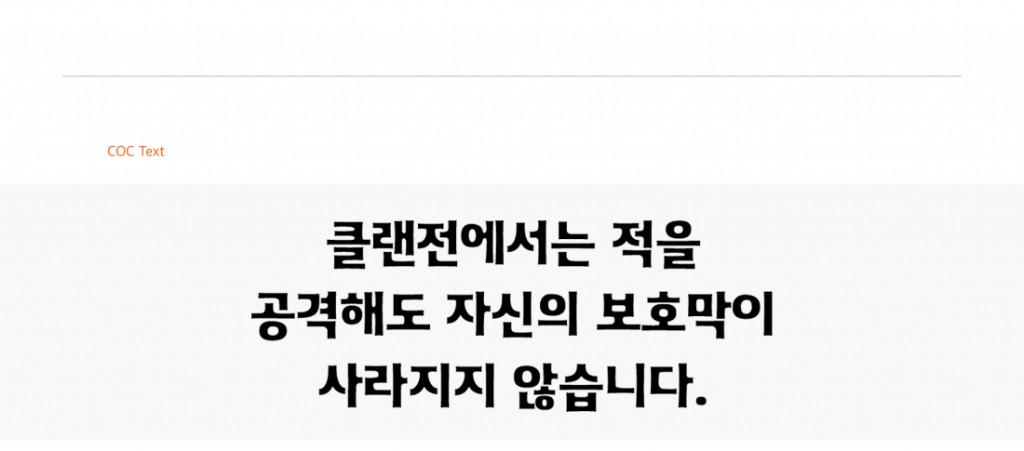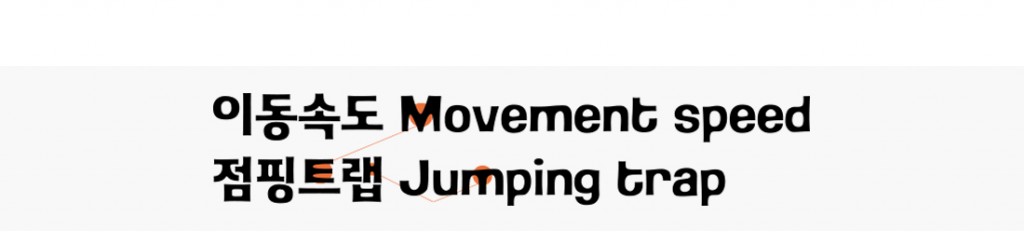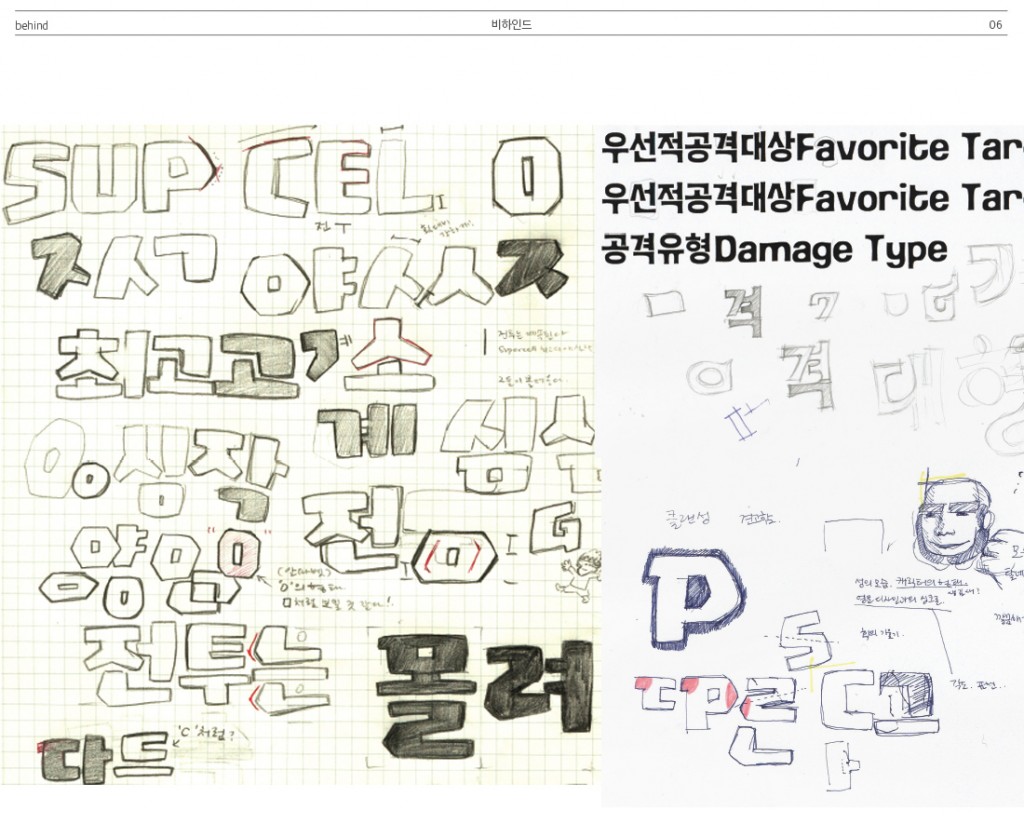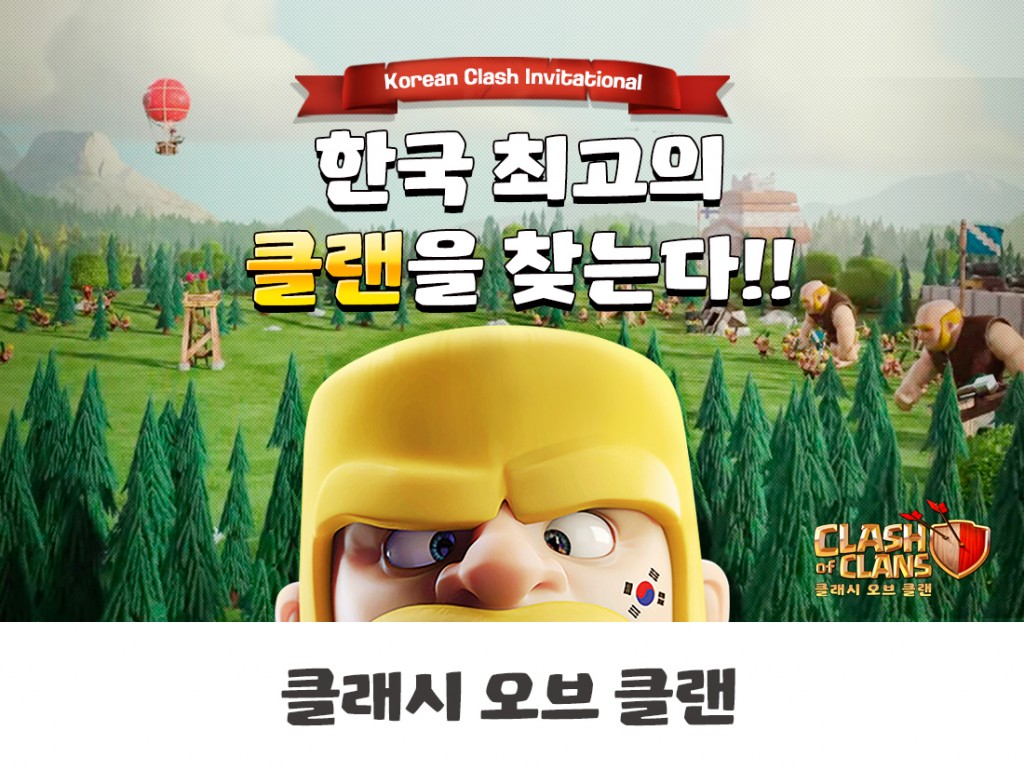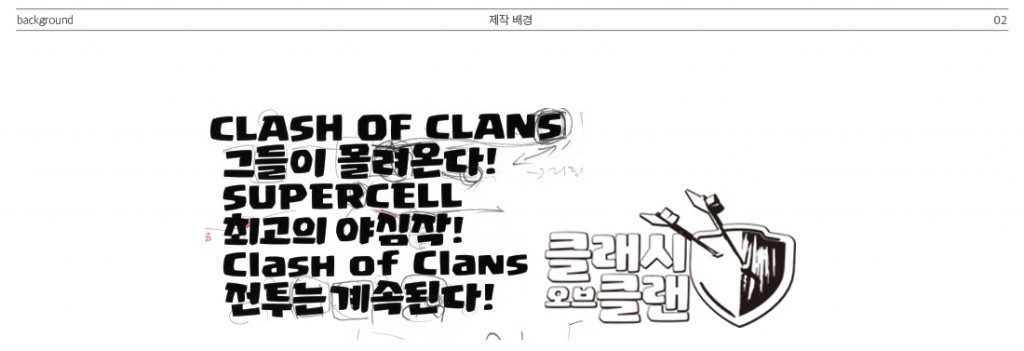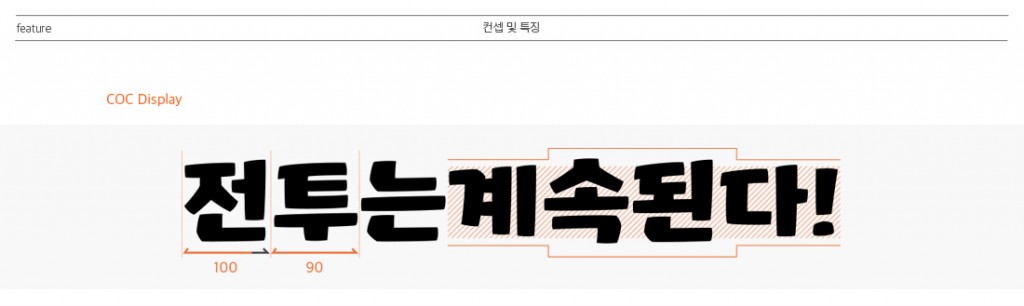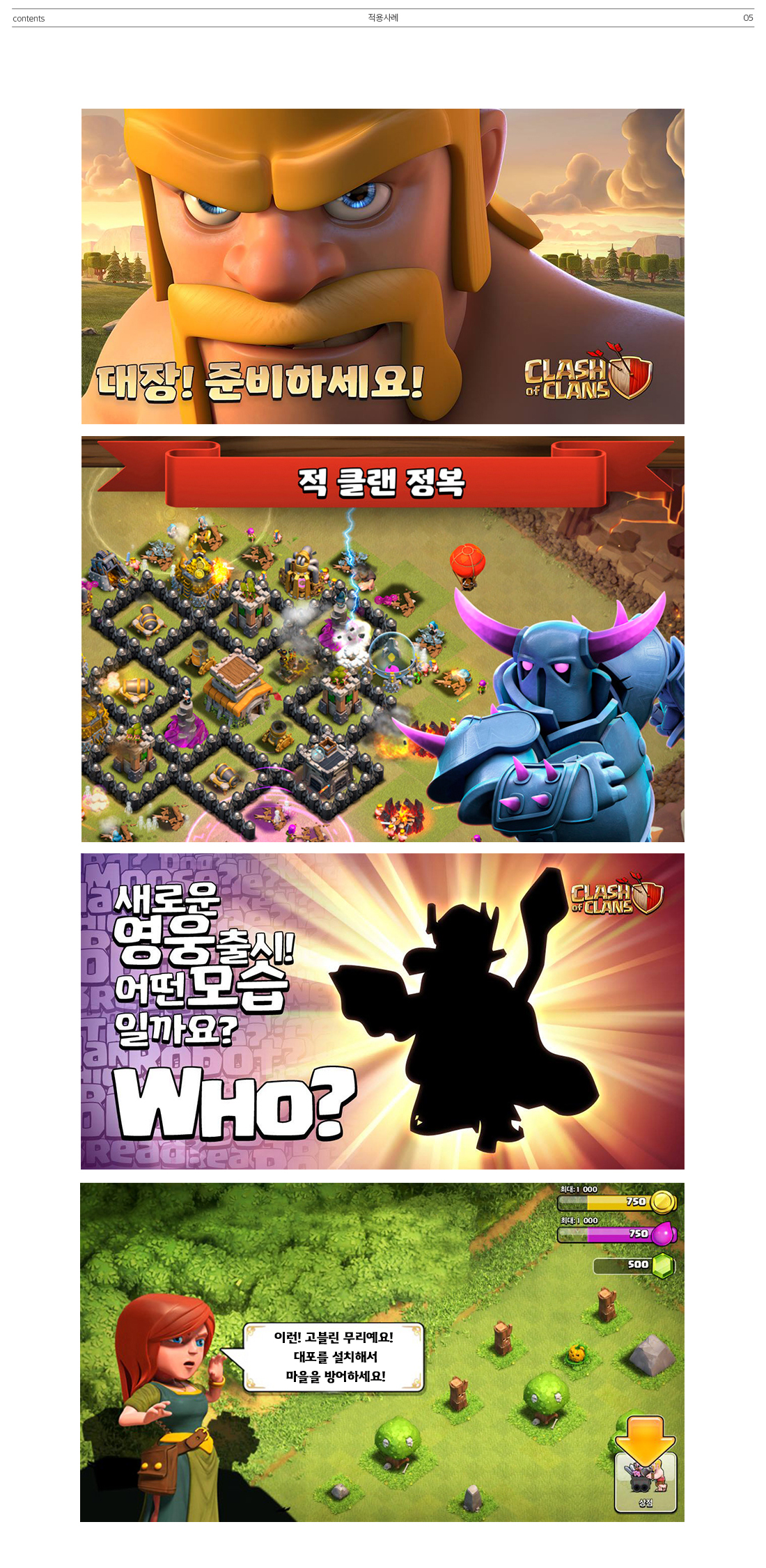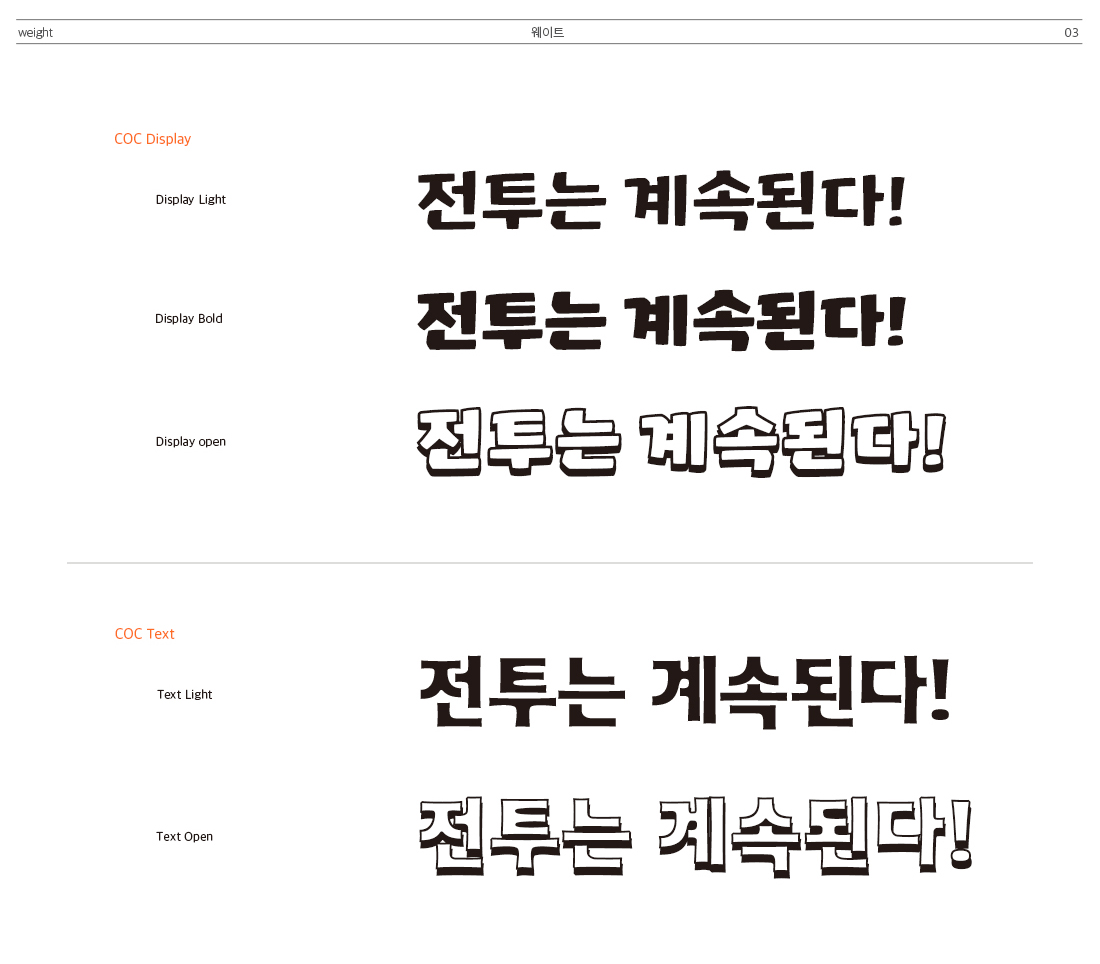
클래시 오브 클랜 : 전투는 계속된다. 폰트도 계속된다!
재치있는 광고나 그래픽으로 잘 알려진 게임 ‘클래시 오브 클랜‘은, 브랜딩을 위해 영문전용서체를 개발하여 효과적으로 사용하고 있었다. 다만, 한글 전용서체는 따로 가지고 있지 않아 게임에서 뿐만 아니라 마케팅에서도 게임의 매력을 잘 살리지 못하는 한계가 있었고, 이를 극복하기 위해 한글 전용서체 제작을 산돌에 의뢰하여 프로젝트가 진행되었다.
타이포브랜딩 : 클래시 오브 클랜 전용서체
클래시 오브 클랜의 전세계적인 히트로 모바일 게임업계를 평정한 슈퍼셀(SUPERCELL). 슈퍼셀은 핀란드의 게임회사로 클래시 오브 클랜 뿐만 아니라 붐비치, 헤이데이 등의 게임을 통해 자신들만의 색깔을 확실히 구축해나가고 있으며, 그들의 대표작 클래시 오브 클랜은 출시한 이래 인기순위 상위권을 놓치지 않고 세계 135개국 유저들이 함께 즐기는 게임으로 발돋움했다.
제작배경
재치있는 광고나 그래픽으로 잘 알려진 ‘클래시 오브 클랜’은, 브랜딩을 위해 영문전용서체를 개발하여 효과적으로 사용하고 있었다. 다만, 한글 전용서체는 따로 가지고 있지 않아 게임에서
뿐만 아니라 마케팅에서도 게임의 매력을 잘 살리지 못하는 한계가 있었고, 이를 극복하기 위해 클래시 오브 클랜과 잘 어울리는 한글 전용서체 제작을 산돌에 의뢰하여 프로젝트가 진행되었다.
컨셉 및 특징
# 모듈
글자폭을 가변폭으로 설정하여 세로획이 많은 글자에서도 두께가 고르게 보이도록 했다. 탈네모꼴 형태이고, 시각기준선을 가운데로 정렬해 리듬감이 돋보인다.
# 자소의 특징
ㄹ, ㅂ, ㅇ 등에서 비정형, 비대칭적으로 디자인해 게임의 캐릭터와 분위기에서 느껴지는 이미지를 담았다.
# 라틴 알파벳과의 조화
영문의 곡선과 꺽임 표현, 세리프 등을 한글 디자인에도 적절하게 적용하였다.
# 모듈
제목용보다는 ‘잘 읽히는’것이 우선이므로 기본 고딕의 틀에서 자소가 조금 자유로운 형태의 모듈을 기반으로 디자인하였다.
# 자소의 특징
가독성을 크게 해치지 않는 범위 내에서 라틴 알파벳의 디자인 요소를 반영하여, 거의 모든 획과 획이 만나는 접점 부분을 둥글고 부드럽게 처리하였다 가독성 향상을 위해 곁줄기, 이음줄기, 이음보는 이웃한 자소와 붙지않게 디자인하였다.
# 라틴 알파벳과의 조화
영문의 개성을 한글자소에 적용하여, 획의 굵기가 고르지 않은 데에서 느껴지는 리듬을 유사하게 표현하였다. 하지만 한글 특성상 영문보다 복잡한 구조이기에 H, M 등에서 나타나는 강한 뭉침은 완화하였다. 자소의 맺음도 수직, 수평으로 표현하였다.
클래시 오브 클랜의 한글 디자인이 게임의 분위기와 잘 어울리게 하기 위해서 산돌 직원들끼리 클랜을 만들고 다같이 게임을 하면서 아이디어를 주고 받았던 과정이 기억에 남는다.
COC Display 폰트는 가로획과 세로획의 두께 대비가 강하다는 특징을 가지고 있다. 이런 특징을 잘 살리기 위해 글자폭을 고정폭이 아닌 가변폭으로 설정하였다. 그 이유는 세로모임꼴 글자에 비해 가로모임꼴 글자들(특히 ㅐ,ㅔ 계열이나 쌍자음 계열의 글자)이 세로획이 많아 그 공간을 고정폭에서는 확보하기 어려웠기 때문이다. 그래서 글자들이 전체적으로 고른 두께와 일관된 인상을 줄 수 있도록 각 계열마다 제각기 다른 폭을 설정해서 제작하였다.
국문 폰트명 : 클오클 Display / 클오클 Text
영문 폰트명 : COC Display / COC Text
제작 구분 : 신규
클라이언트 : SUPERCELL
디자인 디렉팅 : 이도경
폰트 디자인 : 박부미, 김수진, 강민재, 강주연, 김초롱
웨이트 : 클오클 Display 3종 / 클오클 Text 2종
글자 구성 : 한글 11,172자 / 영문 / 약물
출시년도 : 2015